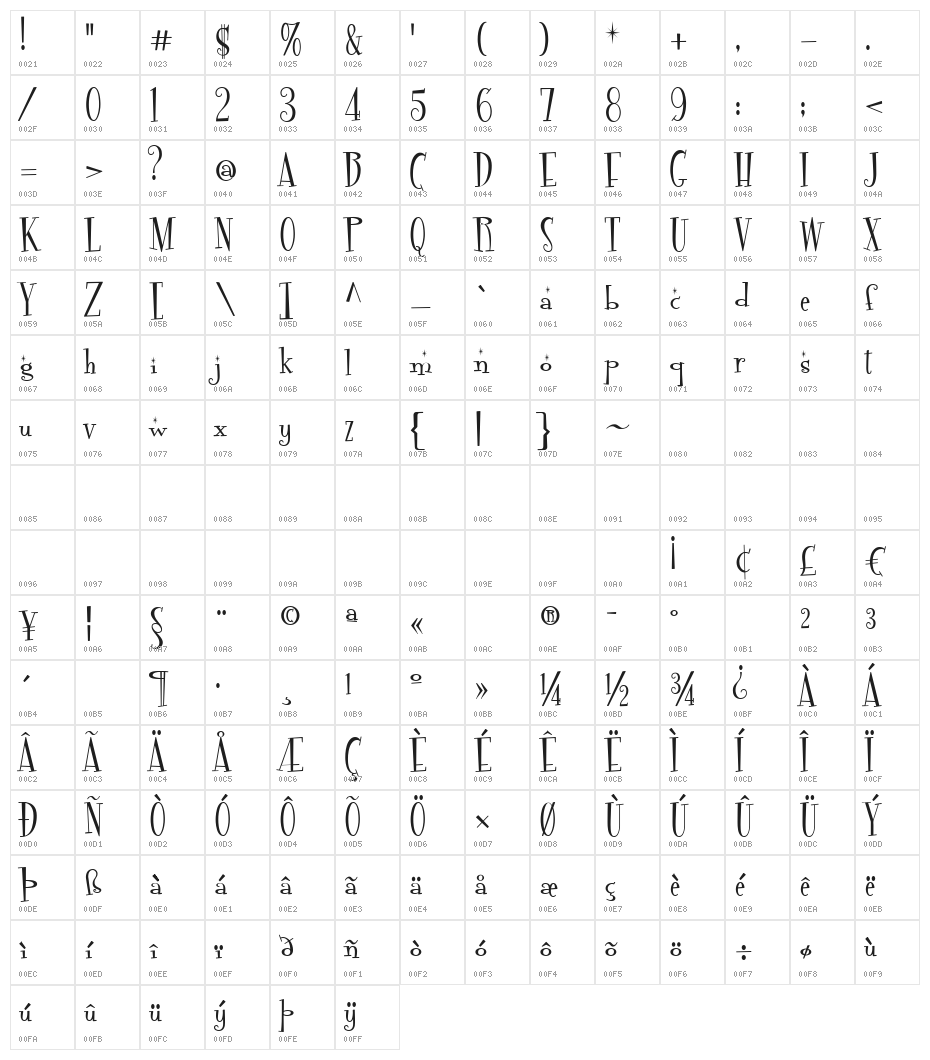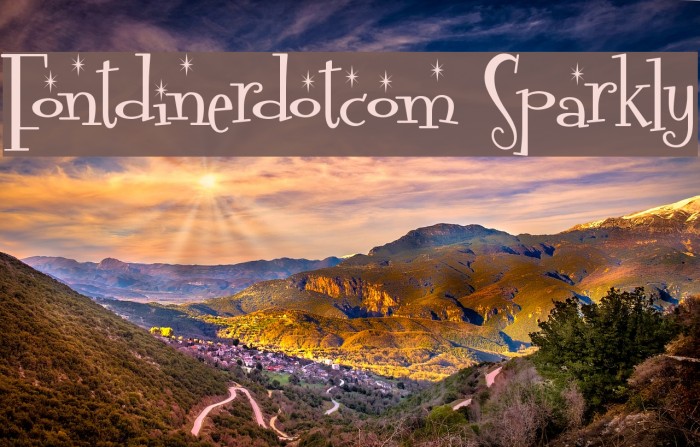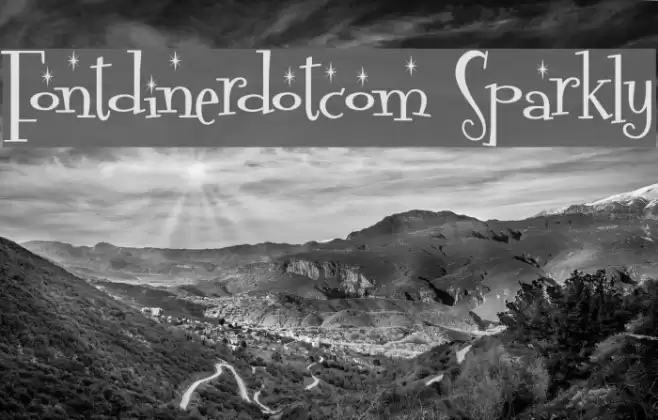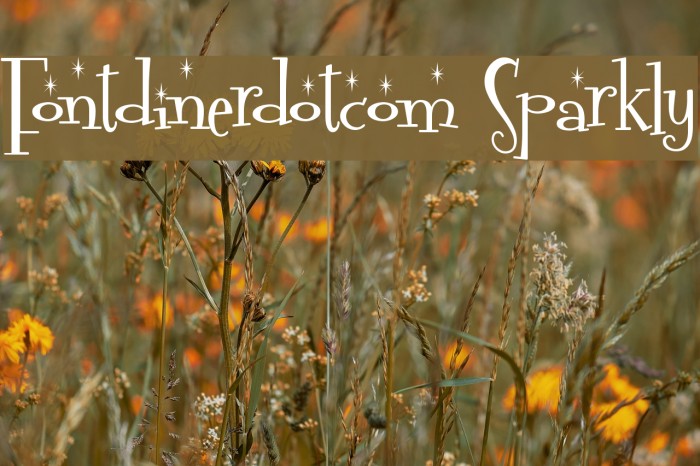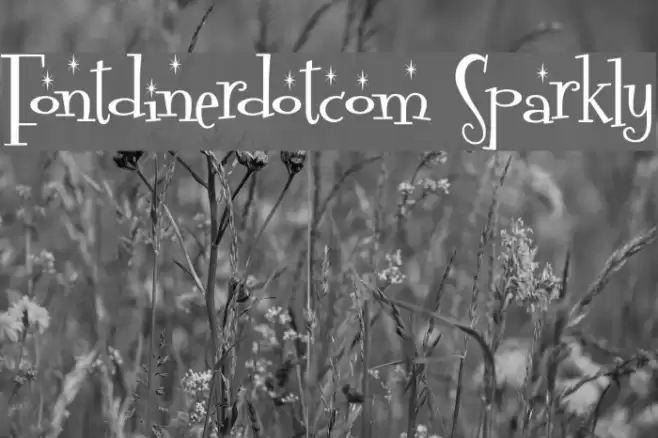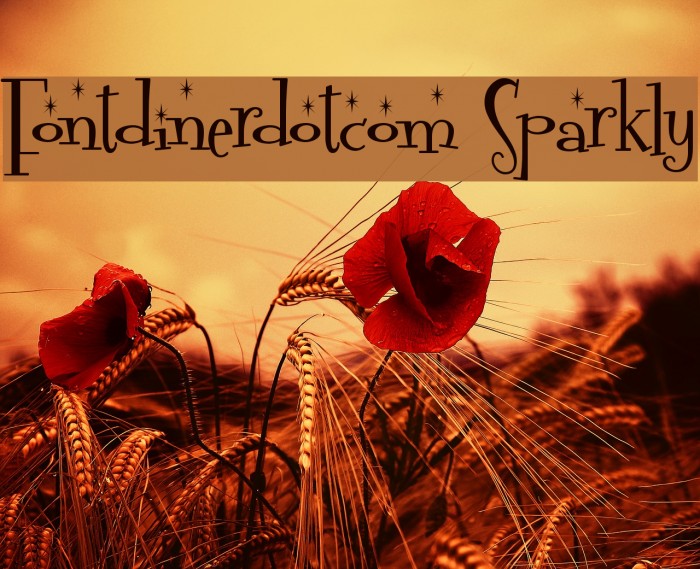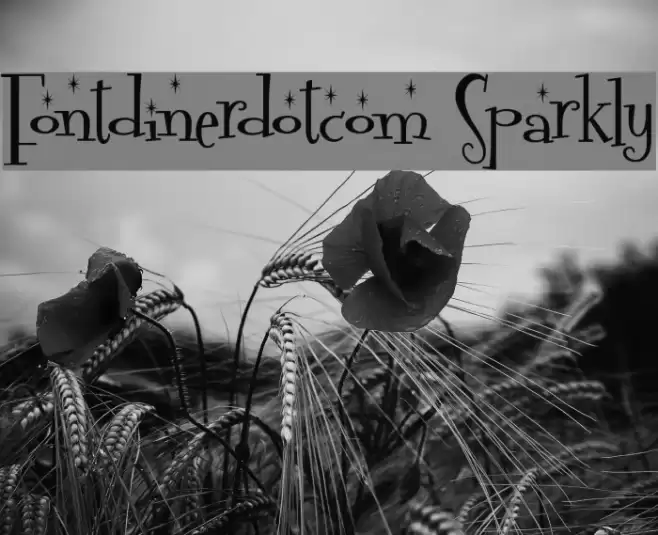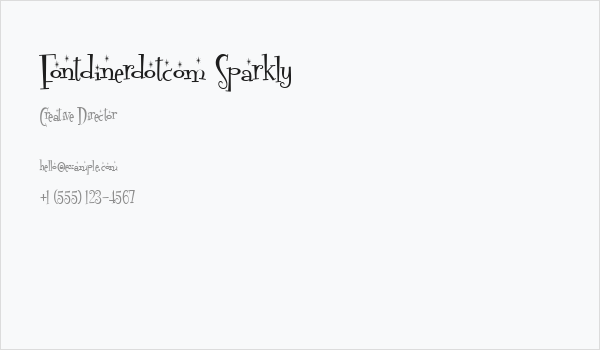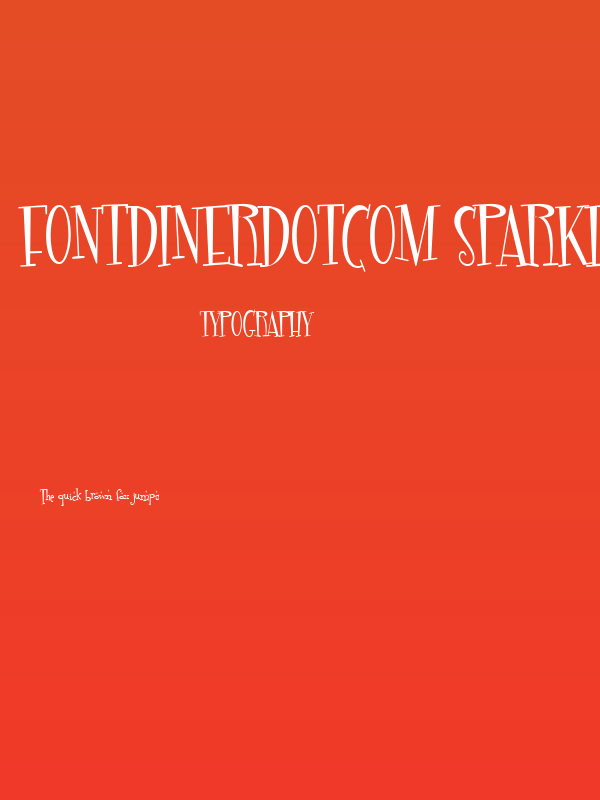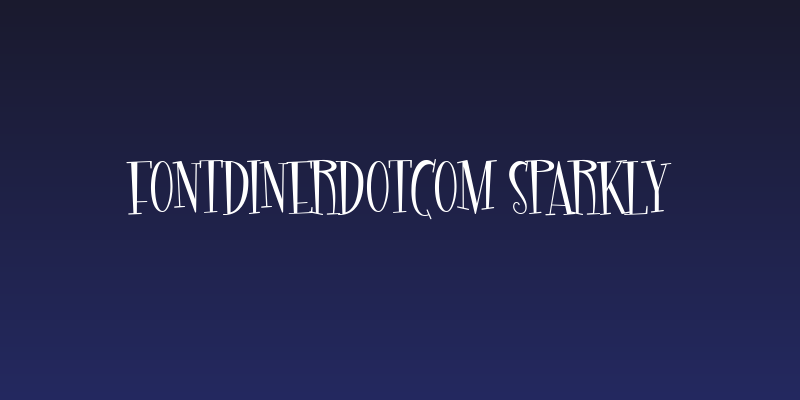
Fontdinerdotcom Sparkly Font
| Gesamtstil | Vintage, Decorative |
| Vorgeschlagene Projekte | Ideal for vintage-themed posters, playful invitations, children's book covers, and retro branding projects. |